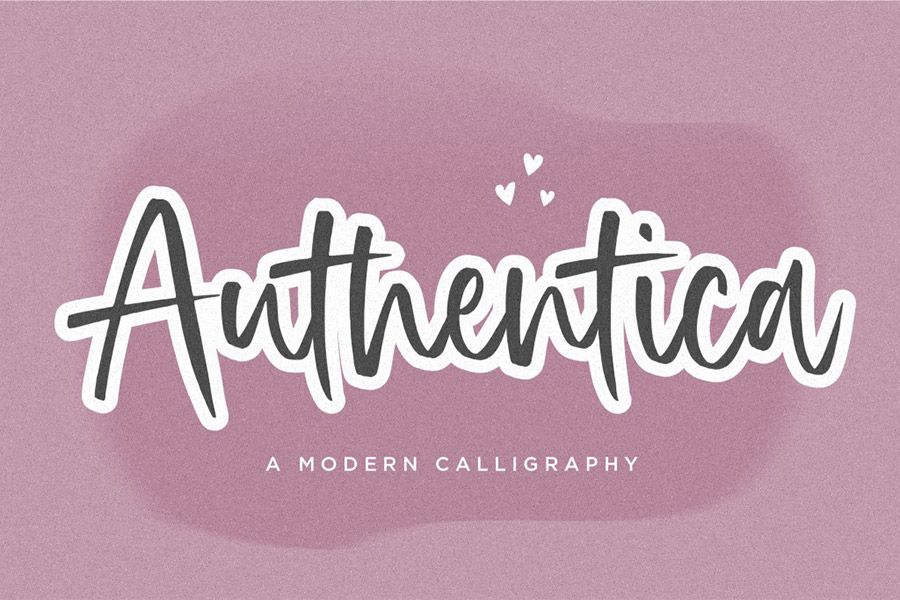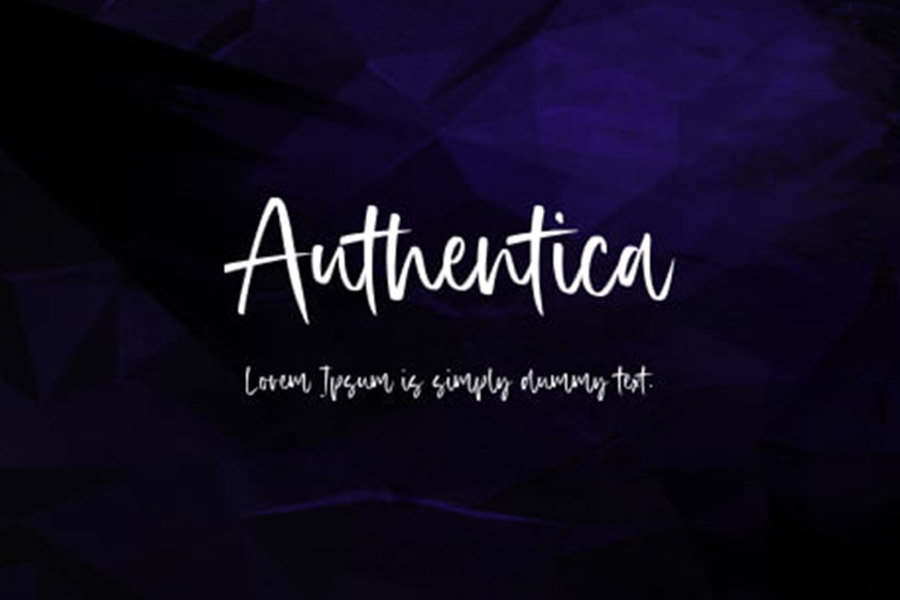
Authentica Regular là một font chữ cho Photoshop đẹp và hiện đại. Do đó, font chữ này rất được ưa chuộng khi sử dụng trong các thiết kế tối giản và thanh lịch. Để cho phép bạn thoải mái sáng tạo, Authentica cũng cung cấp các tính năng OpenType.
Font chữ Authentica Regular là một trong những lựa chọn tuyệt vời cho các nhà thiết kế khi sử dụng Photoshop. Với phong cách viết tay mềm mại, thanh lịch và độc đáo, font này giúp các thiết kế của bạn thêm phần thu hút và khác biệt. Hy vọng với những chia sẻ và hướng dẫn chi tiết trong bài viết của Hubservices, bạn có thể dễ dàng cài đặt và sử dụng font Authentica Regular một cách hiệu quả trong các dự án thiết kế của mình.